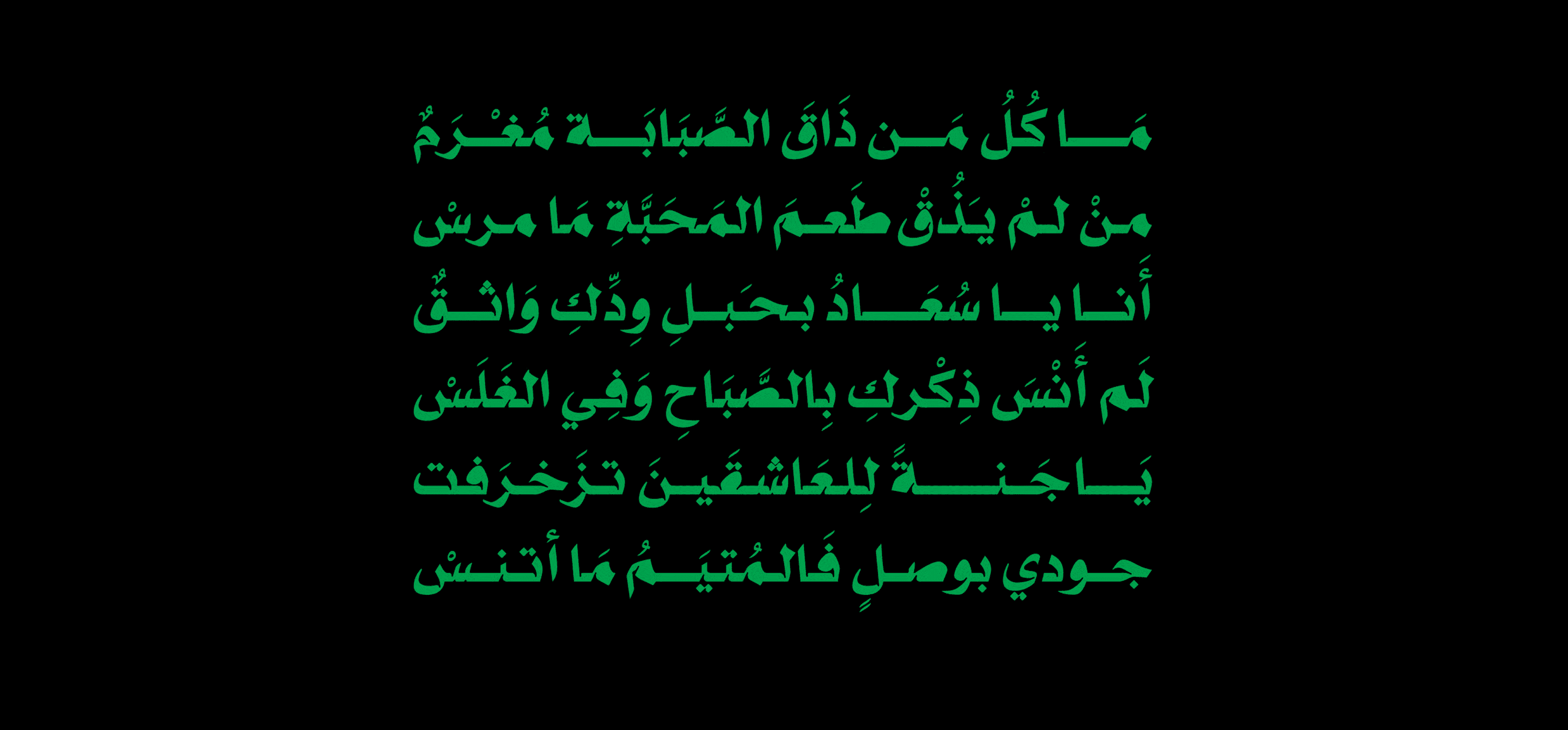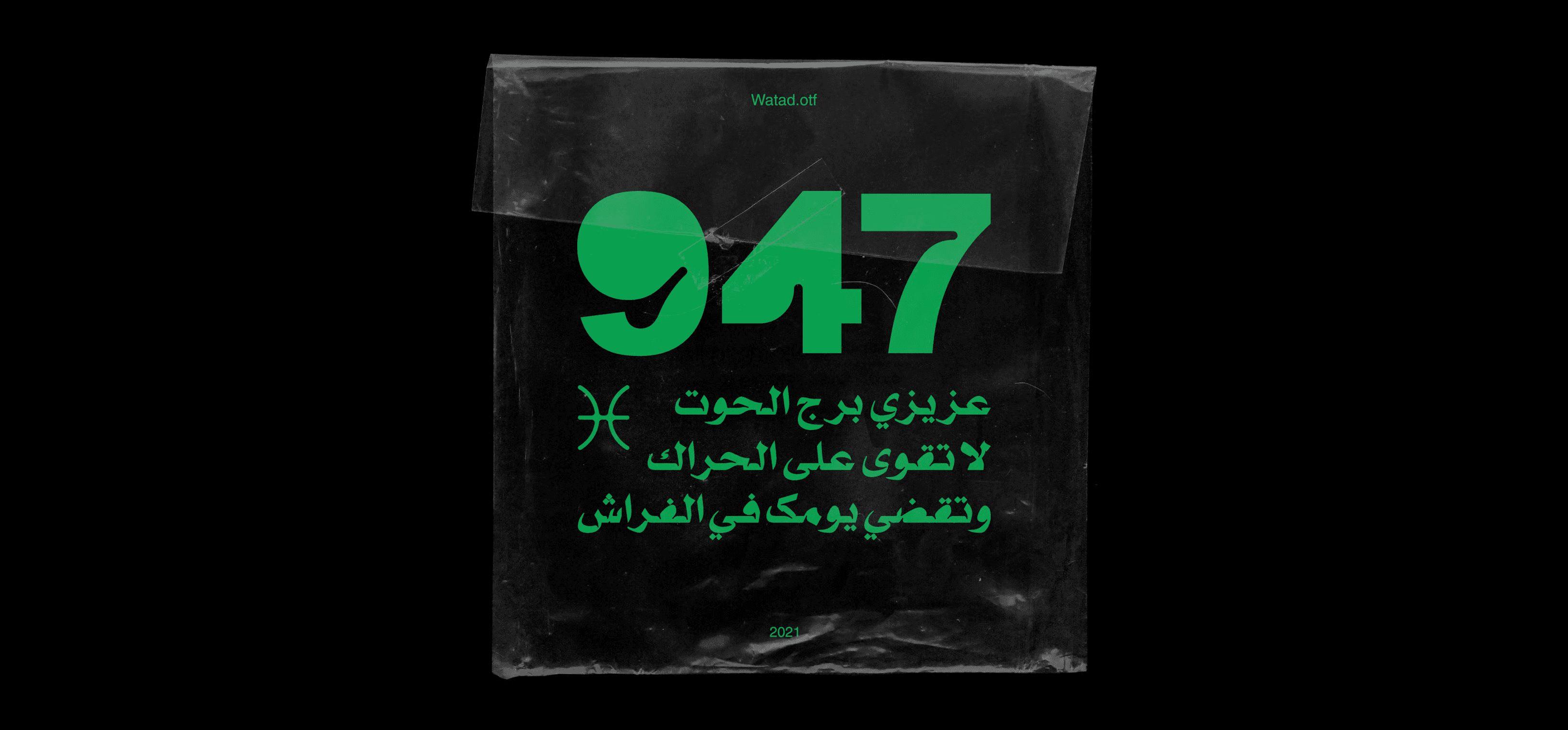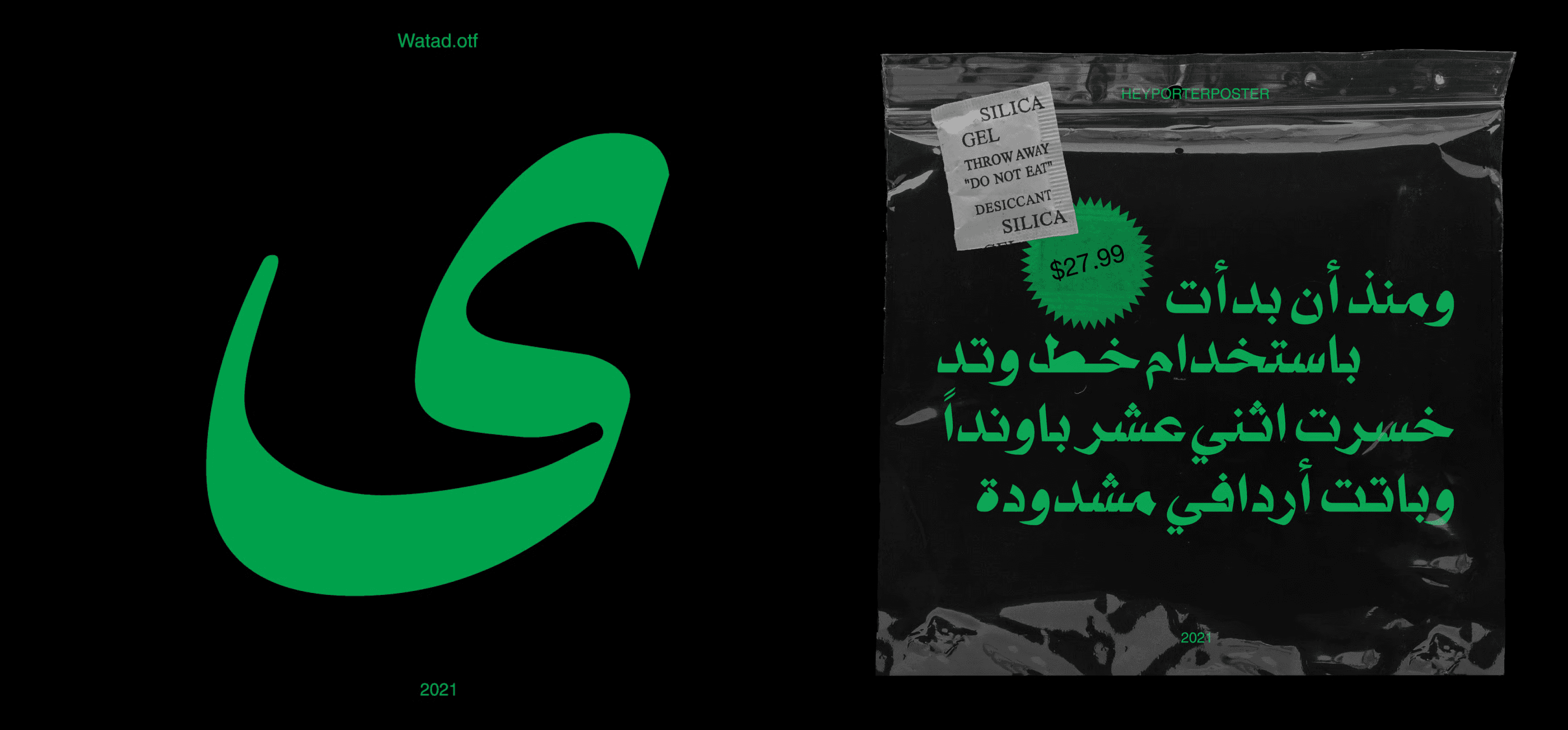
هو خط عرض عربي يتميز بأشكال حروف نسخ حادة ومعاصرة، مع تفاصيل نظيفة لمصائد الحبر تمنحه مظهر الخط العربي التقليدي وإحساس القوالب المستقبلية. مناسب للعناوين أو النصوص القصيرة إلى المتوسطة."